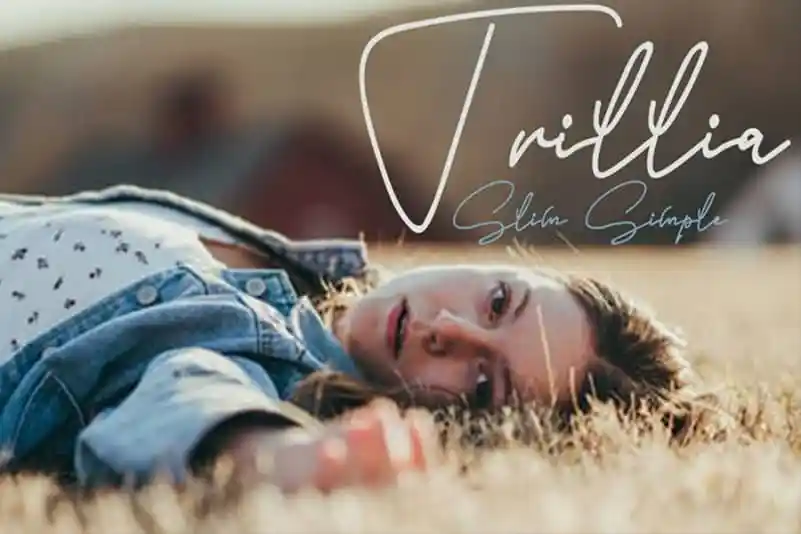
Slim Simple Script Font – Download Grátis
A Slim Simple Script Font é uma maravilhosa fonte feita à mão que mantém sua influência clássica na tipografia, ao mesmo tempo que se atualiza e se faz moderna e fresca. Esta versatilidade a torna ideal para um leque amplo de ideias criativas, seja em cartões de visita e títulos ou em estação móveis. A inermediaSTUDIO trouxe esta fonte simplesmente perfeita que traz o charme da escrita feita à mão para qualquer projeto gráfico, sem esquecer do atualismo e da modernidade que tornam a Slim Simple Script Font uma escolha inteligente para designers de todo mundo. Engane-se se pensasse que só pode ser usada em cartões de visita ou estação móveis; esta fonte oferece flexibilidade suficiente para transformar qualquer projeto, desde o design de ícones até o layout da web.